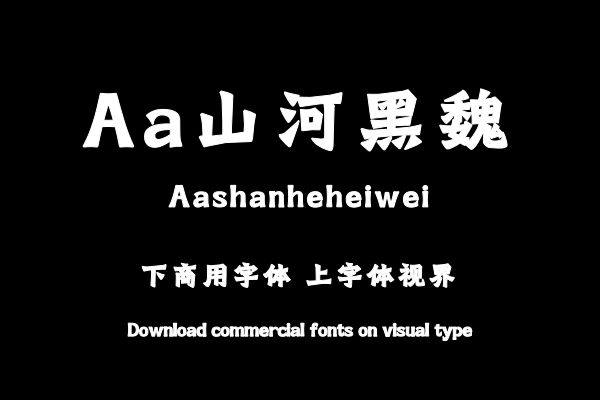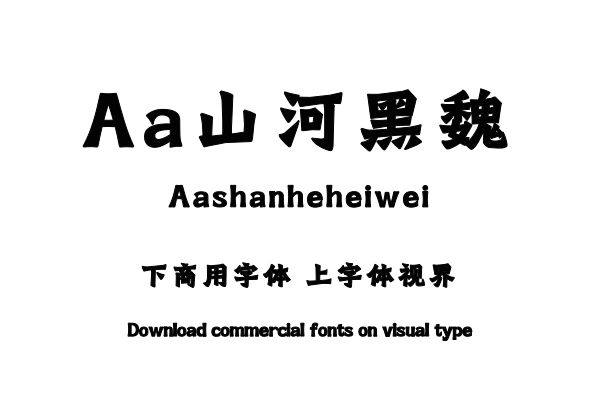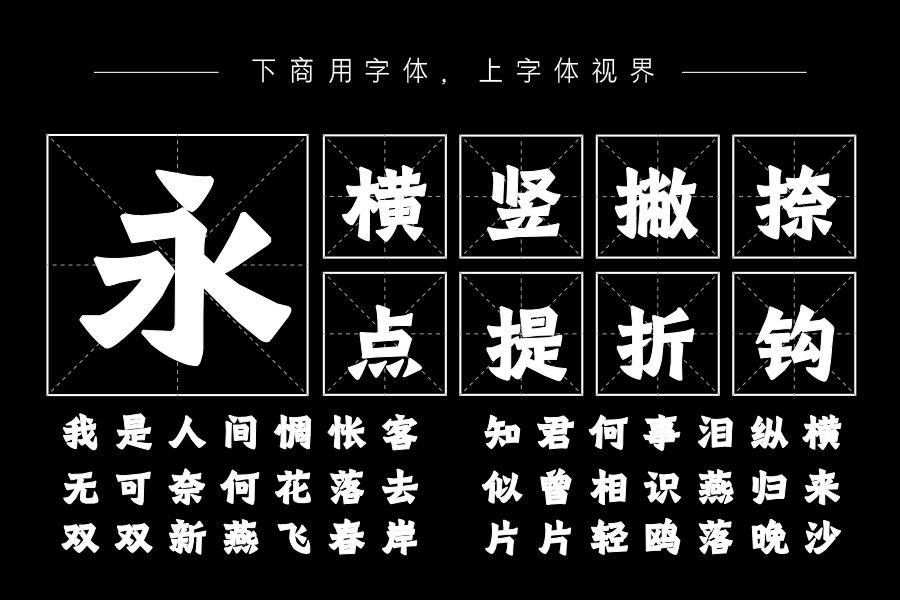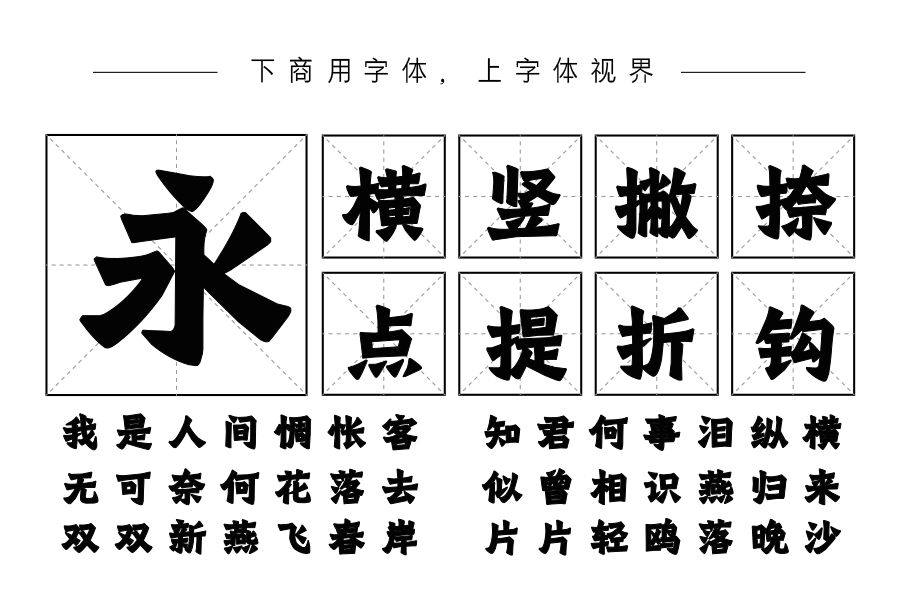
这款字体以《魏灵藏造像记》为设计参考,《魏灵藏造像记》为魏碑中方笔带锋的典型代表,笔画锋颖外露,结体扁方紧密,点画厚重饱满,显的雄劲非凡,端庄隽洁。购买须知:“下载服务费”与“字体VIP”所获得字体 仅用于个人非商用, 商用请联系付费授权。本字体为电脑用字,手机没有root权限不支持直接手机换字(手机如何root,请自行百度搜索教程)。购买前请先 了解清楚后再付款 ,字体为虚拟产品无法回收 一旦购买不支持退款。